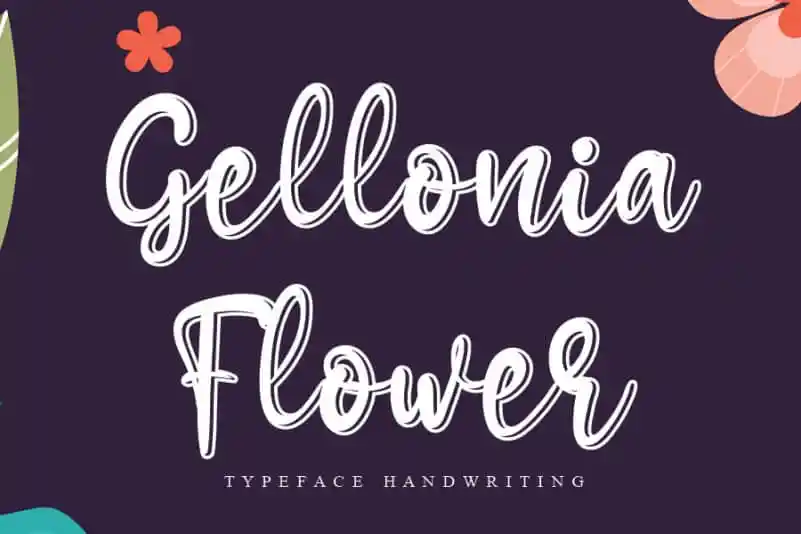
Gellonia Flower Script Font – Download Grátis
A Gellonia Flower Script Font é uma tipografia escrita a mão leve, que traz consigo alegria e amizade para qualquer projeto. Ela se destaca como um girozinho leve, perfeitamente adaptada a logos, marcas de marca, redes sociais e até mesmo projetos DIY criativos. Esta fonte é uma excelente opção quando você busca algo que seja único e divertido ao trazer um toque elegante aos seus trabalhos digitais. Ideal para aqueles buscando tornar suas publicações mais interessantes e pessoais, a Gellonia Flower Script Font não deixará ninguém indiferente. Com seu charme e originalidade, essa fonte certamente será um grande aliado para designers que buscam uma maneira de personalizar suas criações em um estilo único. Desde pequenos detalhes como logotipos até grandes projetos de arte digital, a Gellonia Flower Script Font oferece a oportunidade de manter seu trabalho diferenciado e encantador, tornando-a perfeita para qualquer tipo de projeto que você possa estar trabalhando.